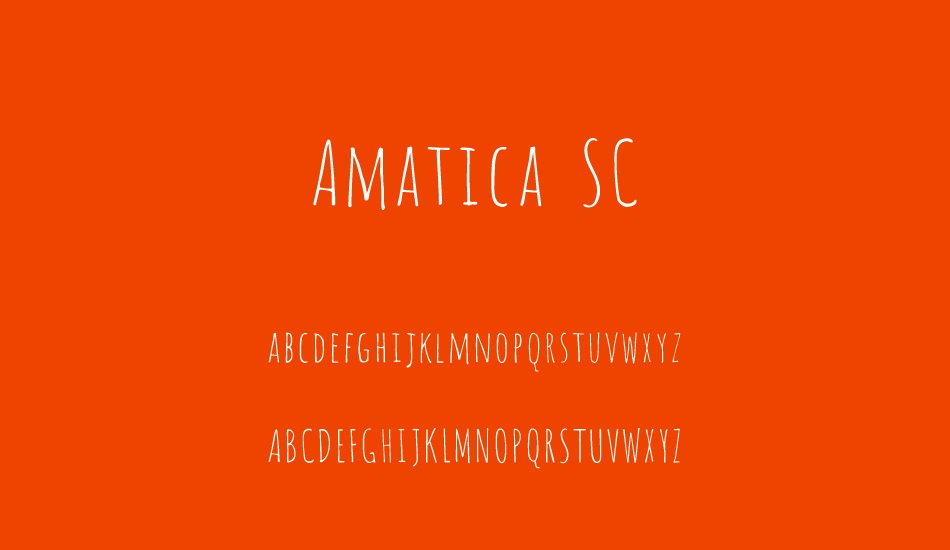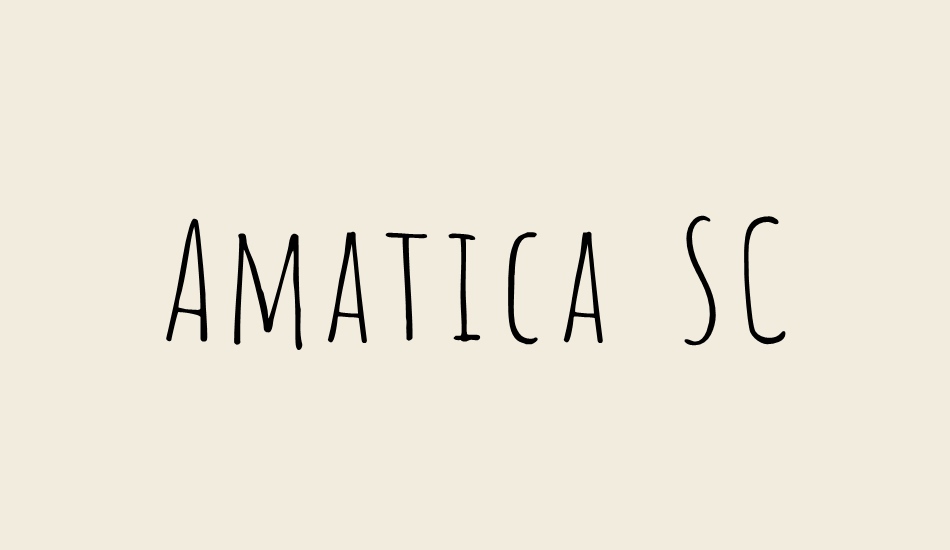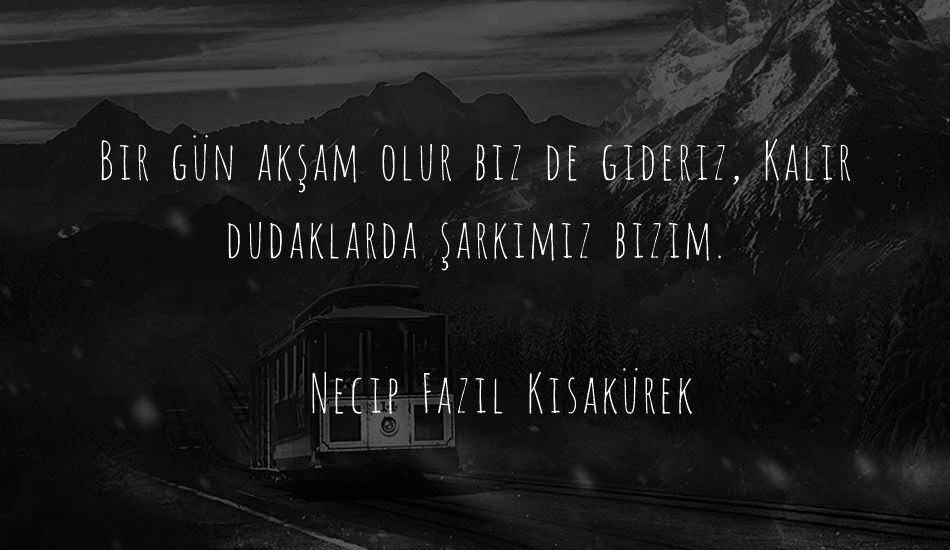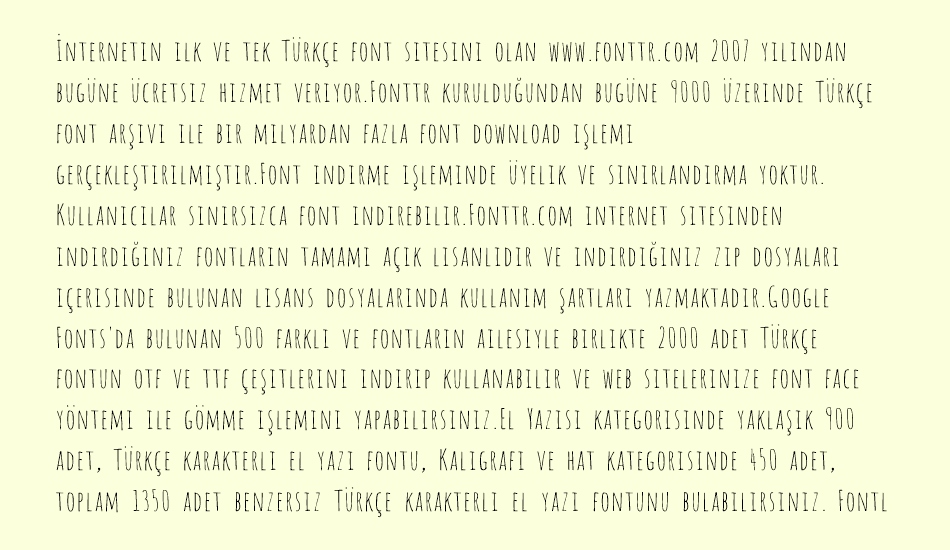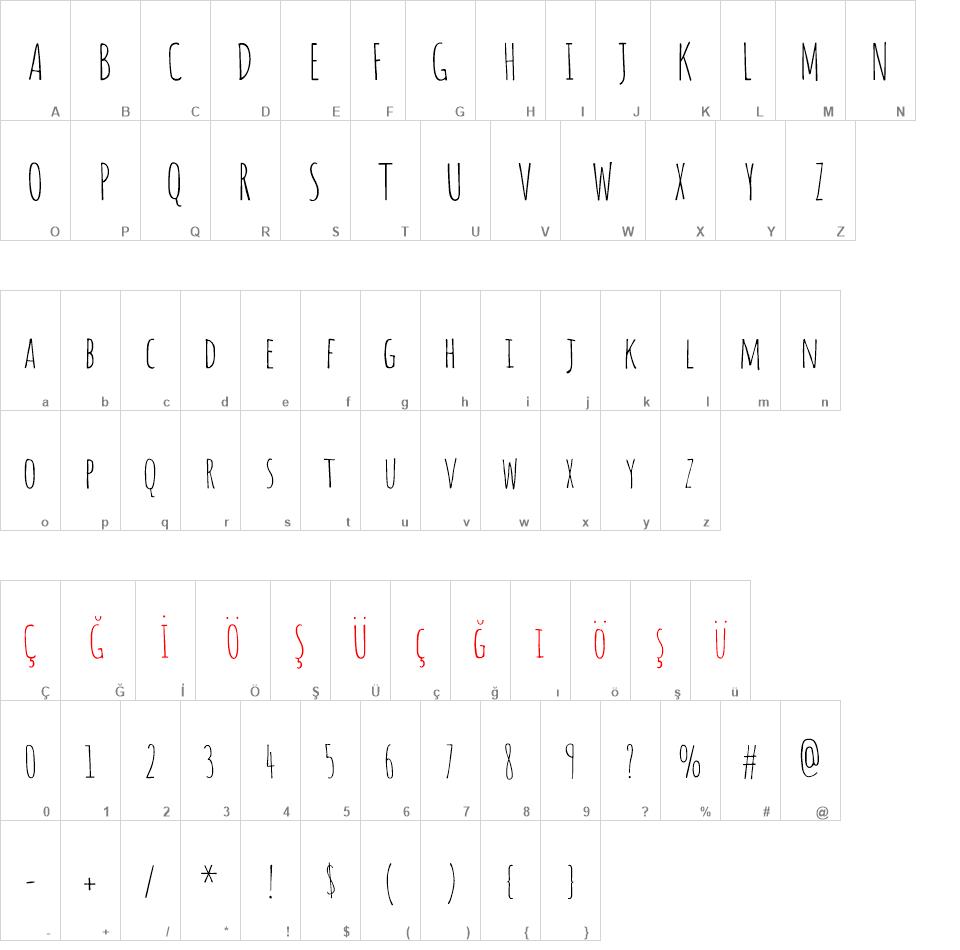
Eğlenceli insanlar için eğlenceli bir yazı tipi! Amatica SC, Vernon Adams tarafından popüler Amatic SC ailesinin bir atılımı olarak başladı. İsrailli bir tasarımcı olan Ben Nathan, İbranice bir bileşen ekledi ve özellikle birçok İbranice'ye uyacak şekilde harf aralıklarını genişletmek için Latin'leri birçok yönden düzeltti.
Amatica SC font